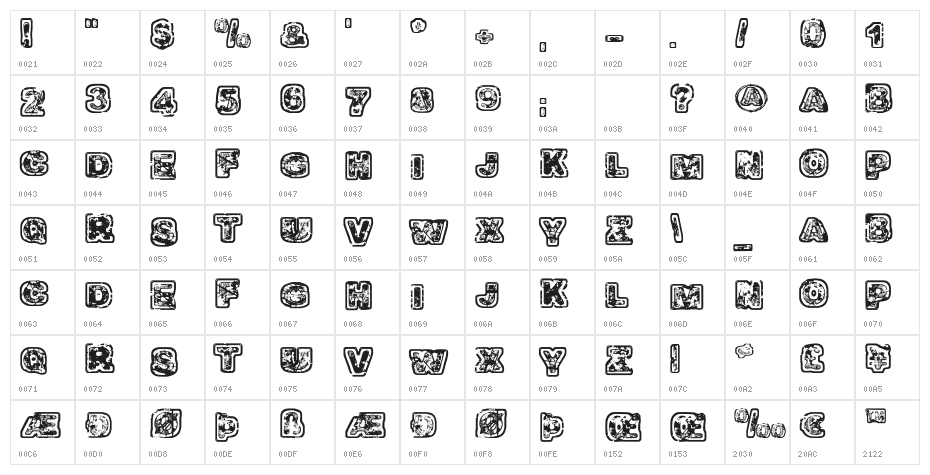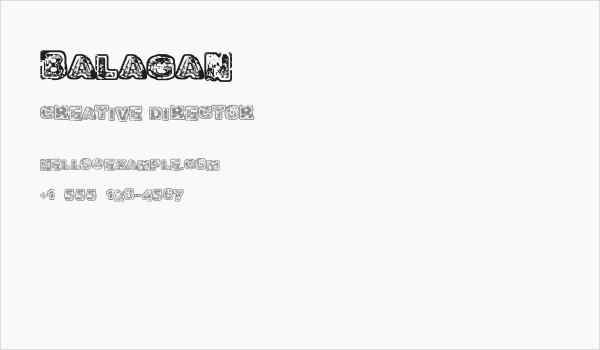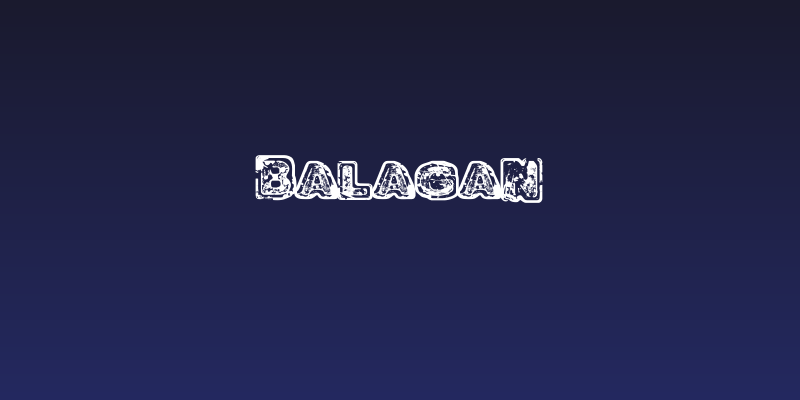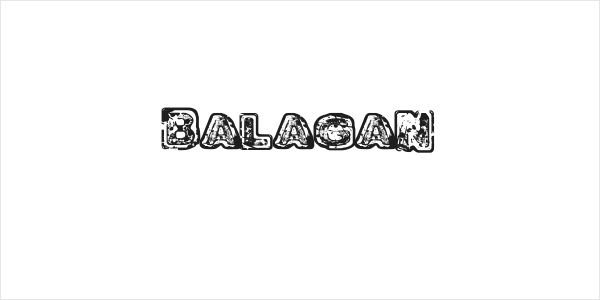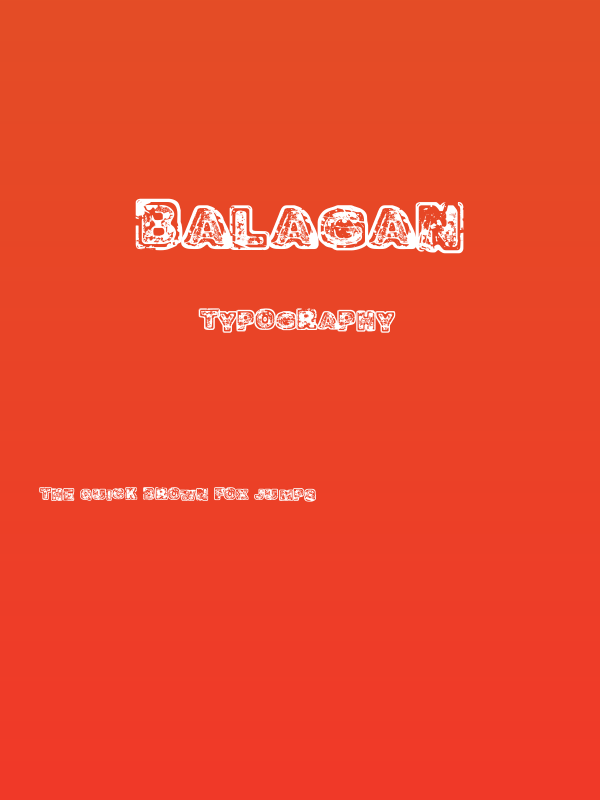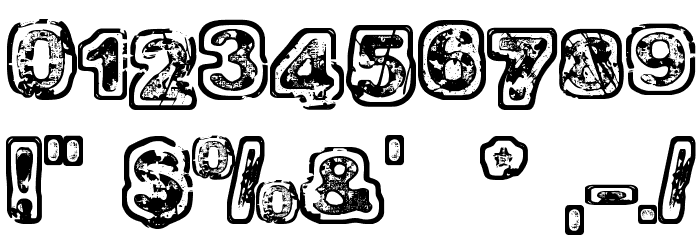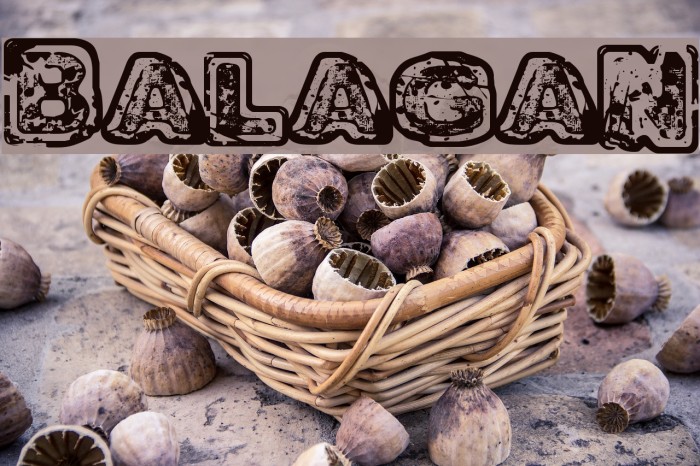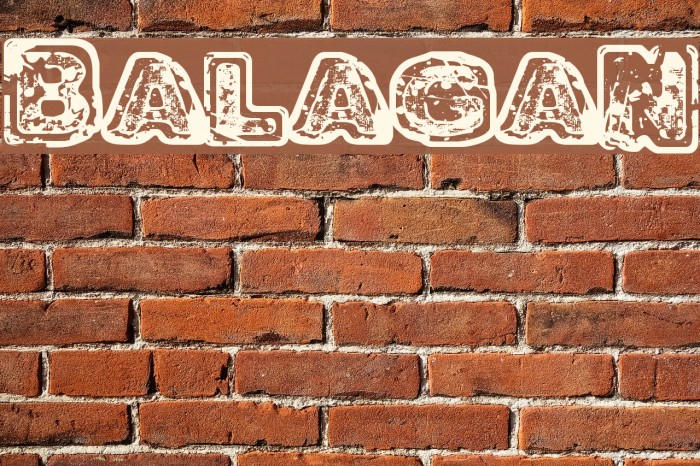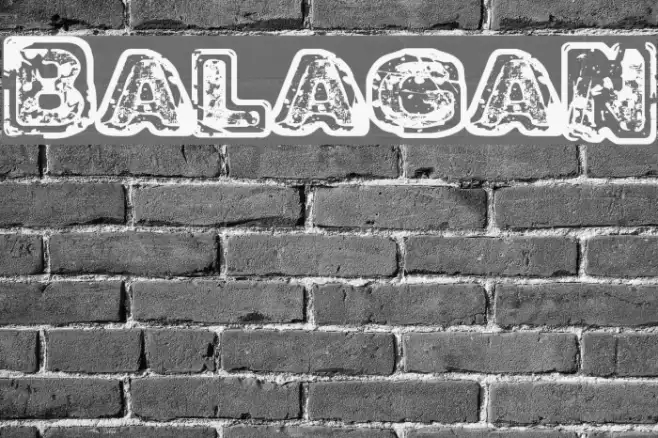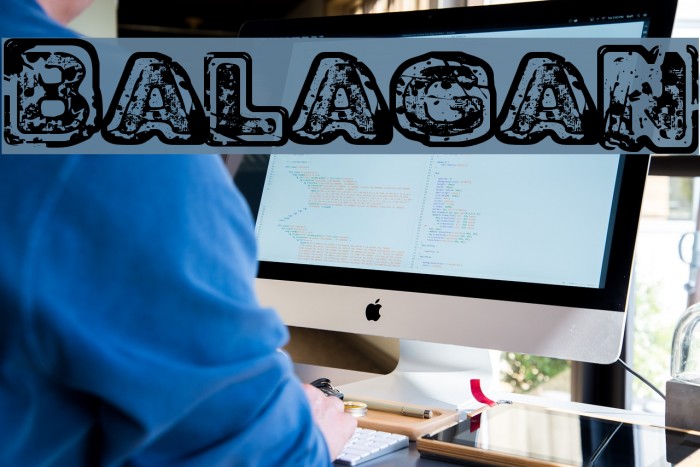
Balagan Font
✎ Messy
| Categorie | Messy |
| Stile generale | Grunge, Urban, Artistic |
| Caso d'uso | Headlines, Posters, Branding |
| Progetti proposti | Ideal for music album covers, posters, streetwear branding, and urban-themed designs. |